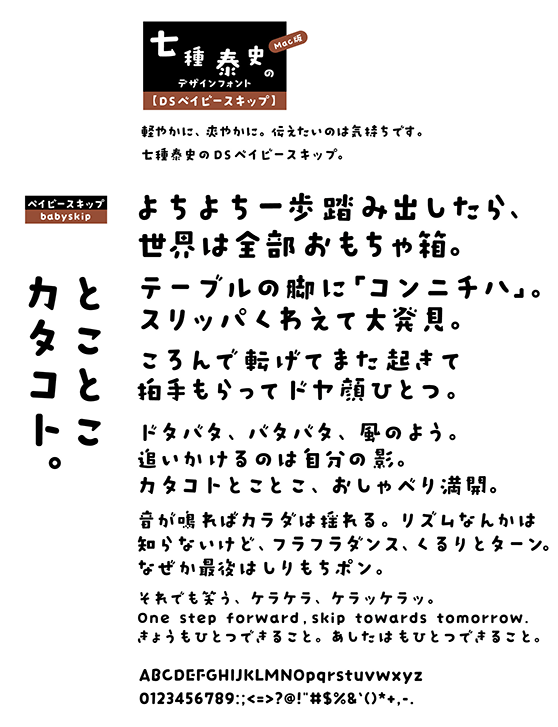
DSベイビースキップ (DS-babyskip)
DS-babyskip
明るく、楽しく 跳ねる、踊る。やさしい動きのある書体です。
七種泰史/デザインシグナルの紹介
こころのこもった文字創りを目指す七種泰史氏のオリジナルブランド「デザインシグナル」。2008年夏からスタートし、年に2~3書体のペースで開発を進行中。多くのファンが新作を心待ちにする人気のブランド。